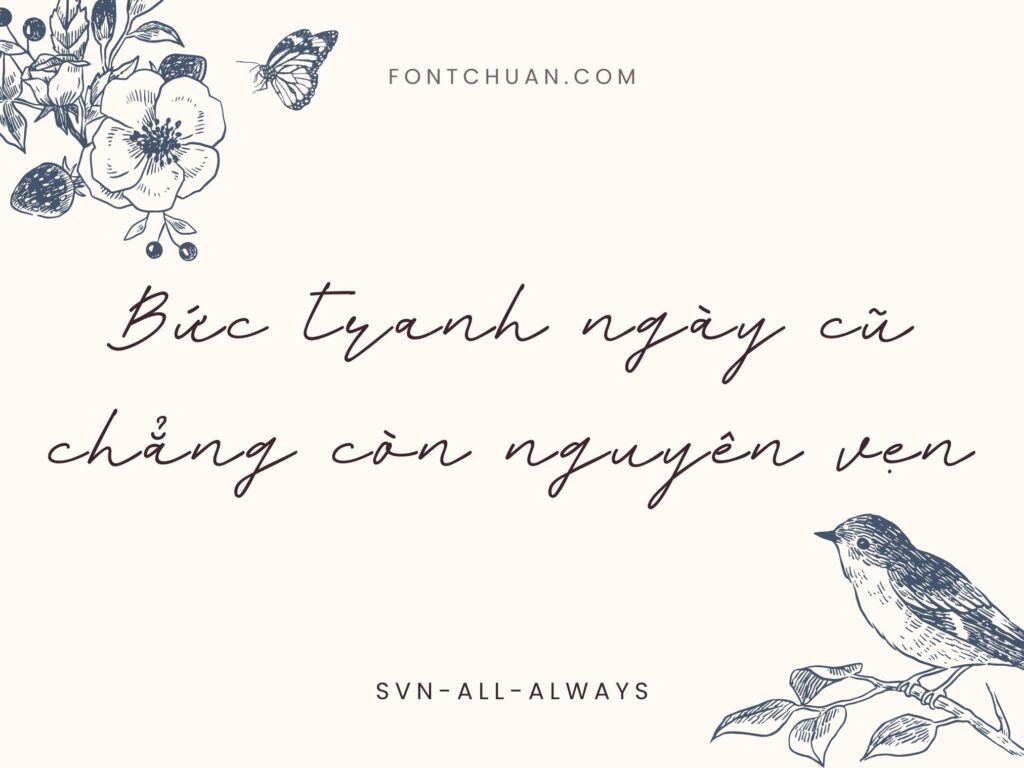
Font SVN All Always Việt Hóa
Font SVN All Always là phiên bản Việt hóa của kiểu chữ All Always, được thực hiện bởi Styleno.1 Fonts. All Always là một font chữ viết tay được thiết kế bởi Khurasan Studio, mang phong cách tự nhiên và thân thiện, tạo cảm giác như một ghi chú viết tay thực sự. Font này thích hợp cho nhiều mục đích sử dụng khác nhau, từ thiết kế thiệp mời, bao bì sản phẩm đến các ấn phẩm truyền thông.
SVN All Always lý tưởng cho các dự án thiết kế yêu cầu sự gần gũi và cá nhân hóa. Font này có thể được ứng dụng như một Font chữ spa, giúp các thương hiệu chăm sóc sức khỏe, làm đẹp và spa thể hiện sự tinh tế, mềm mại và thư giãn trong từng thiết kế. Đồng thời, font cũng phù hợp cho các ngành ẩm thực và thiệp cưới, tạo điểm nhấn nổi bật cho thiết kế. Nhờ sự linh hoạt, SVN All Always còn thích hợp cho các sự kiện như Tết, Valentine, Sinh nhật và các lễ hội khác.